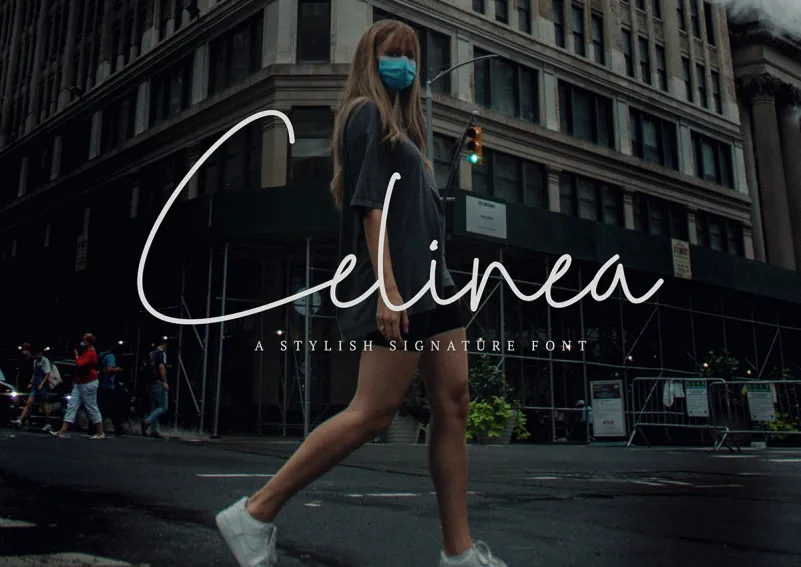
A Celinea Font é uma elegante caligrafia monoline que surge do talento inigualável de novan esthi. Suave e vital, esta fonte se destaca como um escolha perfeita para tornar seus projetos ainda mais atraentes e vivos. Com sua simplicidade única e seu toque carregado de emoção, é ideal para aplicação em várias áreas, desde criações fotográficas até selos ou qualquer outro tipo de projeto que deseje realçar. Esperamos que a Celinea Font possa ajudá-lo a alcançar seus objetivos criativos, seja ele trazendo vida à sua próxima linha editorial, destacando seu trabalho gráfico em uma campanha publicitária ou simplesmente tornando seu design de marca mais atraente.